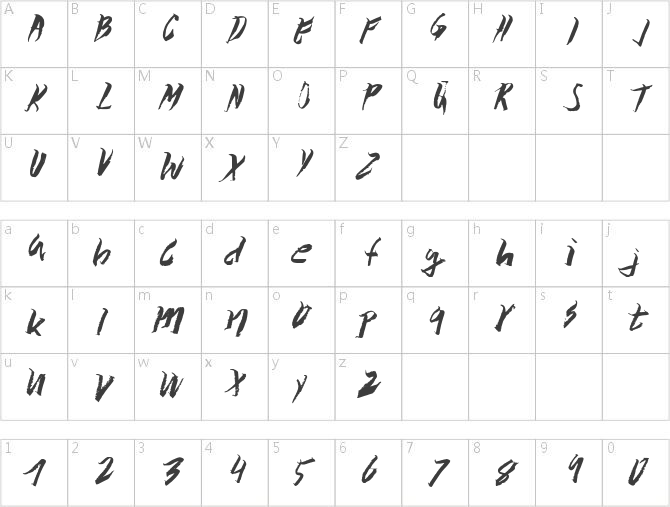
Wolvos 詳情頁
字體名稱: Wolvos
Wolvos
Wolvos介紹
Wolvos字體字庫是一款讓人賞心悅目、百看不厭的英文字體,適合各類廣告和產(chǎn)品包裝設(shè)計應(yīng)用,字體大小0.1MB,格式為ttf字體,上傳用戶是志誠設(shè)計,作者/版權(quán)方為未知
Wolvos效果圖